Растрові, векторні і контурні шрифти
растрові шрифти
Перш ніж розглядати, шрифт з точки зору операційної системи, розберемося з тим, яким чином в принципі може бути представлена (і представляється в дійсності) інформація про шрифт.
Зображення символів шрифту (як і будь-яка інша) на екрані дисплея є растровим зображенням, тобто складається з пофарбованих в Різні кольори точок, або пікселів (pixels). B разі тексту таких кольорів тільки два - колір символу і колір фону. Якщо умовно позначити точку, забарвлену в колір символу, одиницею, а в колір фону - нулем, будь зображуваний на екрані символ можна представити у вигляді прямокутної таблички з нулів і одиниць - бітової карти (bitmap), o яку вже йшлося під час обговорення растрирования. Природно, що кількість елементів в таблиці однозначно
пов'язане з розміром символу на екрані - для малювання символу висотою 12 пунктів (1 pt = 1/72 дюйма і точно відповідає розміру пікселя для більшості типів моніторів) потрібно мати Bitmap висотою 12 рядків, для символу в 8 pt - в 8 рядків. Таблиця, що містить всі 256 бітових карт символів для деякого накреслення і деякого розміру, називається bitmap font (bitmap-шрифт). Ha Малюнок 5.1 показано, як виглядає літера «Q» bitmap-шрифта при великому збільшенні (тонкі білі лінії позначають кордону пікселів).
Малюнок 5.1 Літера bitmap-шрифта
Bitmap-шрифт є найбільш зручним для відображення на екрані з точки зору швидкості промальовування і витрат ресурсів комп'ютера на обробку. Однак розміри символів на екрані можуть змінюватися - отже, для однієї гарнітури необхідні bitmapшріфти декількох розмірів. Оскільки запам'ятовувати шрифти для всіх можливих розмірів занадто марнотратно з точки зору витрачається для їх зберігання пам'яті (як дискової, так і оперативної), творці розділу підтримки шрифтів в операційних системах пішли на наступний компроміс: для найбільш ходових кеглів (розмірів) створюються окремі bitmap-шрифти , для проміжних розмірів бітова карта кожного символу будується безпосередньо перед відображенням на підставі bitmap з найближчого за розміром шрифту тієї ж гарнітури.
Незважаючи на відчутні втрати часу при перерахунку бітових карт «на інший розмір» і не дуже високу якість відображення проміжних розмірів символів на екрані, для виведення тільки на екран і тільки прямих символів bitmap-шрифтів було б цілком
досить. Проблеми виникають, коли текст потрібно повернути або вивести на «тверду копію», або те й інше разом. Якщо для роботи з екраном, що має дозвіл 72 dpi (точки на дюйм) при відображенні символу висотою 16 пунктів досить запам'ятати бітову карту порядку 256 біт (16 точок по вертикалі, 16 по горизонталі), то для відображення символу того ж розміру на папері при вирішенні 1200 dpi потрібно матриця з 267x267 елементів, або 8911 байт. Помножте цю величину на кількість символів в шрифті (256), на кількість використовуваних вами гарнітур і врахуйте необхідну кількість bitmap для різних розмірів символів, а потім прикиньте, чи поміститься необхідний обсяг інформації на ваш жорсткий диск. Незалежно від отриманого результату, зберігання (і передача) образів символів у вигляді бітових карт, придатних для друку з високою роздільною здатністю, виявляється занадто неефективним способом кодування шрифтів.
векторні шрифти
Можливим вирішенням проблеми масштабування шрифту на високі дозволу є використання векторних шрифтів. Ці шрифти є природним способом визначення накреслень символів для пристроїв типу пір'яних або струменевих графопостроителей (плотерів), здатних безпосередньо відтворювати на носії прямі або криві лінії. B векторних шрифтах кожен символ представлений у вигляді сукупності геометричних примітивів - зазвичай відрізків прямих і дуг окружності, заданих своїми координатами щодо «точки прив'язки» (origin point) символу. Приклад векторного символу наведено на Малюнок 5.2.
Малюнок 5.2 Літера векторного шрифту
Масштабування векторного шрифту проводиться простим множенням всіх координат на відповідний множник. Крім графопостроителей, в кінці вісімдесятих років деякі про-
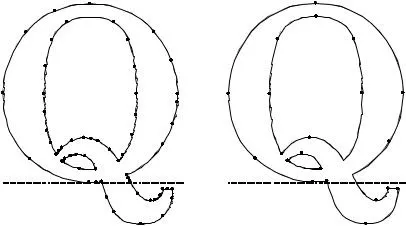
програмних продукти працювали з векторними шрифтами і на дисплеї - можна згадати графічні засоби всіх компіляторів фірми Borland для Dos. Однак для промальовування шрифтів з якістю, придатним для поліграфії, в векторних шрифтах знадобилося б надто велика кількість елементів, що утворюють контуру букв зі змінною товщиною - ці контуру довелося б «набирати» з безлічі тонких ліній. B даний час векторні шрифти використовуються тільки в деяких програмах, пов'язаних з підготовкою креслень.
контурні шрифти
Більш ефективним вирішенням проблеми є використання так званих «outline» (контурних) шрифтів. Іноді їх також називають векторними - це цілком допустимо, якщо тільки виключена плутанина з тими шрифтами, про які йшла мова в попередньому абзаці. Замість запам'ятовування бітових карт, мінливих зі зміною кегля шрифту, запам'ятовуються тільки контури символу (Малюнок 5.3
Малюнок 5.3 Літера TrueType-
При необхідності відобразити на тому чи іншому пристрої символ якогось конкретного розміру бітова карта для даного символу і даного кегля будується шляхом «заповнення» контурів букви точками, розмір яких відповідає дозволу пристрою виведення, тобто проводиться растрирование потрібного символу на відповідний дозвіл.
Для запам'ятовування кривих, які окреслюють межі символів, використовують розбиття кривої (або ламаного) лінії на дільниці і апроксимацію одержані фрагментів кривих полиномами другого або третього ступеня. Ha малюнках межі ділянок, на які розбиті контуру букв, показані жирними точками.
Шрифти TrueType. B залежності від ступеня аппроксимирующего полінома розрізняють два типи outline-шрифтів. Так звані TrueType-шрифти (вони можуть також називатися шрифтами типу 2), спочатку запропоновані фірмою Apple для використання в якості масштабованих екранних шрифтів в комп'ютерах Macintosh в другій половині вісімдесятих років, використовують для формування контуру символів криві другого порядку. Кожна ділянка контуру характеризується, або задається двома точками (кордонами ділянки) і напрямком лінії на кожній з меж. Часто для завдання напрямків використовується третя точка, що лежить на перетині дотичних до кривої на її кінцях (Малюнок 5.5).
Малюнок 5.5 Елементарна крива в шрифтах TrueType (парабола другого порядку)